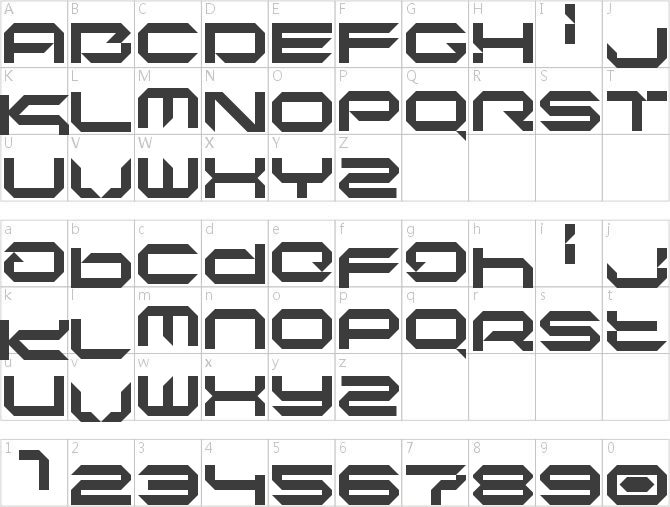
insane_affection_ldr 詳情頁
insane_affection_ldr字體字庫是一款讓人賞心悅目、百看不厭的英文字體,適合各類廣告和產(chǎn)品包裝設(shè)計(jì)應(yīng)用,字體大小0.01MB,格式為ttf字體,上傳用戶是happy,作者/版權(quán)方為未知